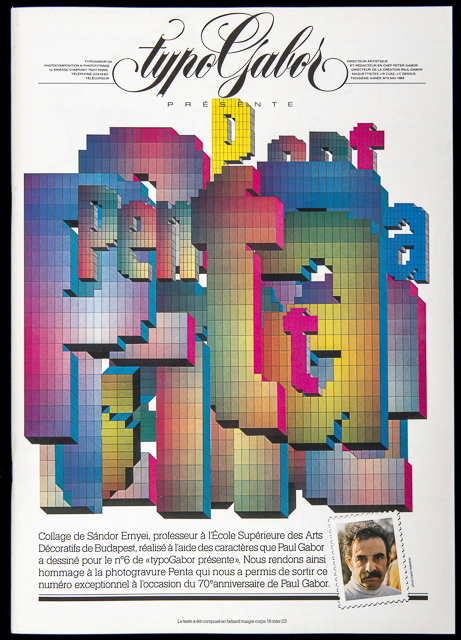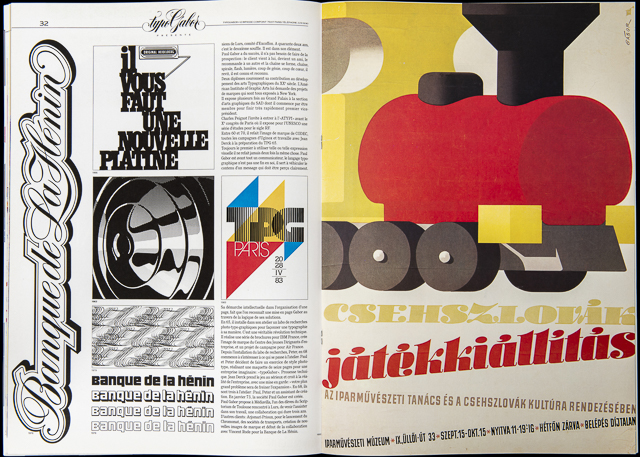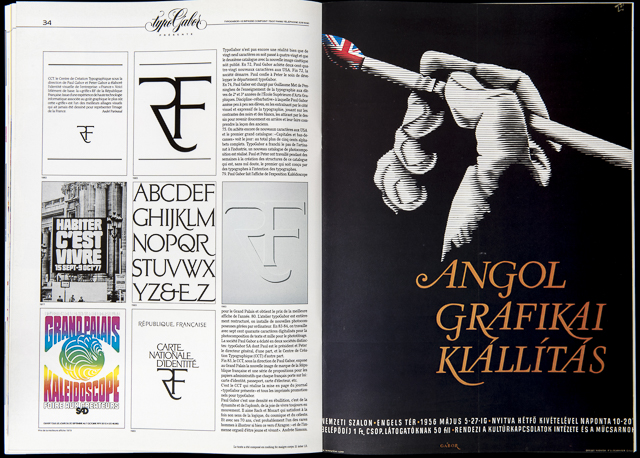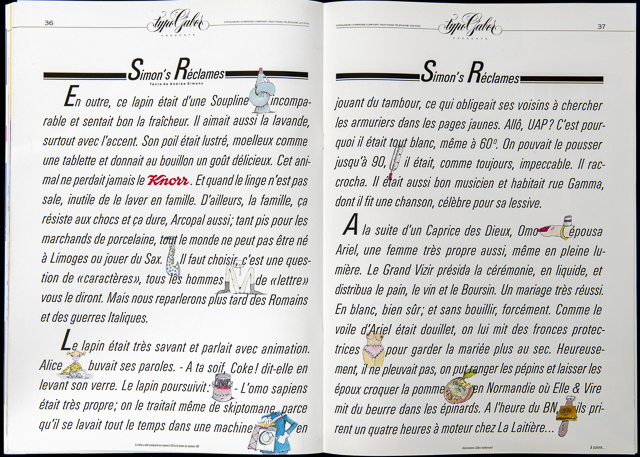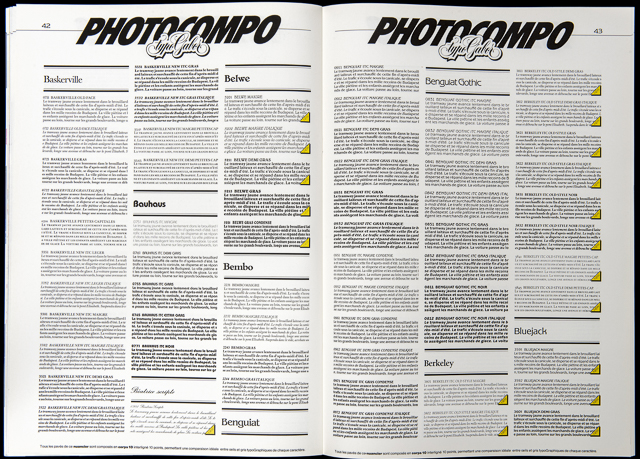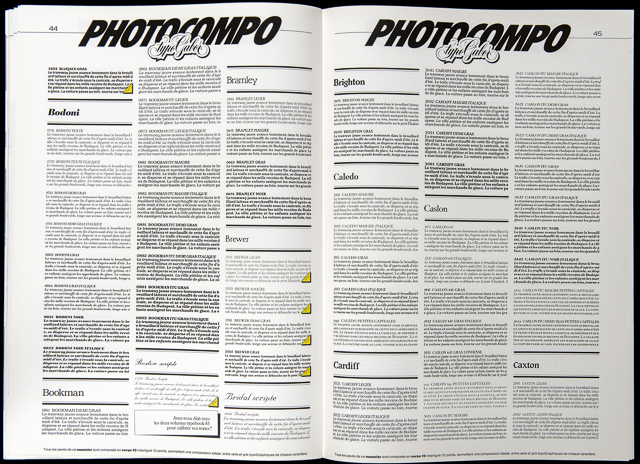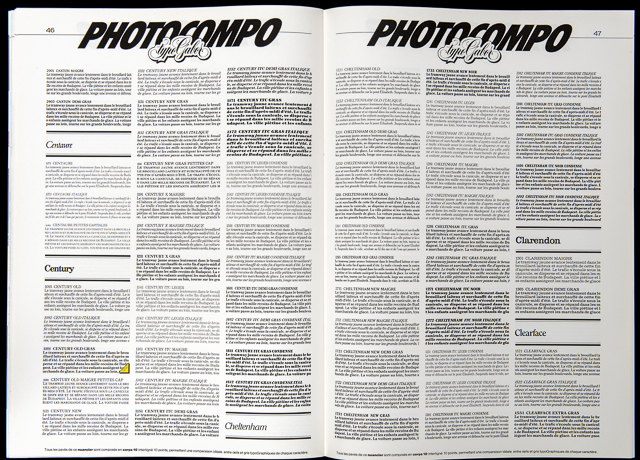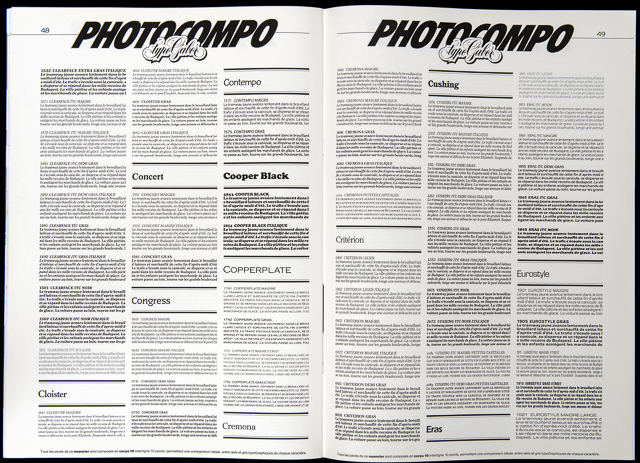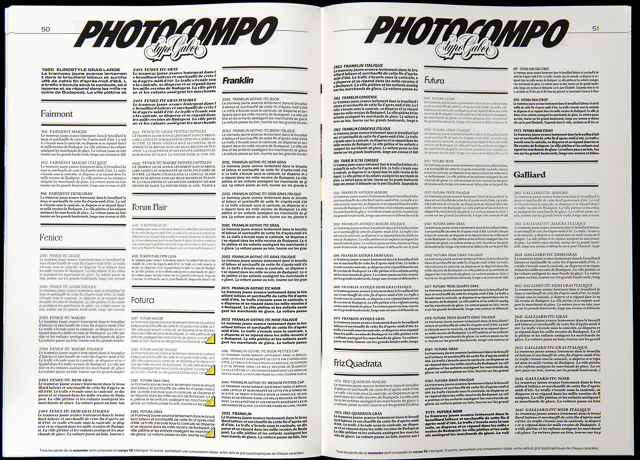
l’Histoire des Magazines typoGabor N°9 Hermann Zapf et Paul Gabor
« TypoGabor présente » N°9 Hermann Zapf et Paul Gabor
Même si certaines manifestations graphiques sont en germe dès 1968, typoGabor est fondée en 1973 par Paul et Peter Gabor. L’activité de la société est double : atelier de création graphique autour des clients historiques de Paul Gabor et société de services typoGraphiques sous l’égide de Peter Gabor.
Les premières années de typoGabor sont rythmées par le fonctionnement coûteux et limité des Diatronic de Berthold. Tant et si bien qu’à la fin des années 1970, la continuité d’exploitation semble compromise. C’est à la faveur d’une annonce dans la revue CARACTÈRE que Peter Gabor découvre l’Alphatype. Il y voit l’amorce d’une révolution du digital. Ce sera son ami (depuis) Raymond Aubry, chef d’Atelier de Graphiservice à Bruxelles qui achèvera de le convaincre. Un système de composition américain venant de Chicago, qui pour la première fois, propose non plus d’acheter mais de louer (prix dérisoire) des polices de caractères, ce qui porte l’offre et la diversité typographiques à un niveau inédit : 1 000 polices contre 80 sur Diatronic auxquels s’ajoutent 16 polices supplémentaires tous les mois.
« typoGabor présente » naît en 1980 de deux constats. Il ne s’agit plus de faire de la Pub pour une entreprise, mais d’informer et d’éduquer un marché. La Publicité. Un marché où s’affrontaient une trentaine de concurrents proposant tous à peu près les mêmes services (24 / 24, coursiers, catalogues de calibrage gratuits et qualité de composition supérieure à celle de l’édition ou de la Presse). typoGabor connaît alors le succès. Les Directeurs Artistiques affluent et les commandes doublent de volume en l’espace de 2 an. Mais la formule marketing du magazine ne plaisait plus à Peter Gabor. Il y préféra une formule nouvelle autorisant toutes les expérimentations typographiques.
Le magazine littéraire de typoGabor était né. Plusieurs directeurs artistiques vont se succéder dans les cuisines typographiques de la maison Gabor. Bill Butt, Jérôme Binda, Philippe Duriez et pour finir Paul Gabor qui revient en 89 par une magistrale œuvre consacré aux Droits de l’Homme. L’Âge d’Homme.
L’expérience de la photocomposition fut de courte durée. Le Postscript arrive sous la forme commercialisée d’Adobe Type Manager et tous les prestataires de composition perdent 50 clients par jour à partir de 1990. Peter Gabor tenta encore d’adapter son entreprise en devenant le premier compositeur qui a basculé la totalité de son fonds sur Macintosh. Mais les dettes s’accumulant et victime d’un administrateur judiciaire peu scrupuleux, il finit par baisser les bras, non sans avoir personnellement créé 4 polices de caractères pour le Journal Libération en 1994.
Une aventure de vie passée à promouvoir la diversité et la qualité de composition, parce que comme l’aimait à rappeler son père Paul, d’après une phrase de Jean Cocteau : « Le style n’est pas une danse mais une démarche ».
L’illustration basée sur l’alphabet « numérique » de Paul a été réalisée par Sándor Ernyei lors d’une visite à Paris (cliquez sur la photo pour voir les détails).
Ce magazine va clore le chapitre des publications « traditionnelles » du magazine « typoGabor Présente ». Il avait quelque chose de tragique pour moi. Mise en œuvre au début de l’année 84 et publié en mai, soit 2 mois 1 / 2 avant le décès de ma mère Klara Gabor le 13 août 1984. Paul quant à lui venait d’avoir une alerte cardiaque en 1983. Ce faisant la famille, ma seule famille se fragilisait et l’immense amour que j’avais pour l’un et l’autre me dictait un devoir de mémoire de leur vivant. J’allais donc consacrer l’édition de ce magazine à l’œuvre de Paul. Mais je me devais de l’équilibrer. Ne voulant pas en faire un livre de deuil mais plutôt une référence à la gloire des grands typographes contemporain. J’ai appelé à la rescousse Fernand Baudin à Bruxelles. Il a écouté et approuvé. Nous avons convenu d’un voyage à Darmstadt pour aller rencontrer à trois (Fernand, Paul et moi-même) Hermann Zapf pour l’interviewer sur son œuvre.
La maison d’Hermann Zapf. Un choc. Une battisse toute blanche, carrée. Construite autour d’un patio sur lequel toutes les pièces donnaient par des vitres. De fait la maison était illuminée autant vers l’intérieur que vers l’extérieur qui donnait sur la lisière d’un bois. Les pièces étaient immenses. On allait d’un espace vers l’autre sans porte, juste des ouvertures. On pouvait évoquer une construction à la Bauhaus, mais aussi bien une maison à la japonaise. Ça n’était pas un musée, mais plutôt un lieu de travail et de réflexion. Hermann nous amena dans son bureau et là il nous reçut et nous donna un cours de typo. Il prit son stylo à bille et nous écrivit un texte en Garamond corps huit avec juste un outil que chacun de nous utilise tant bien que se peut. Mais Zapf avait la maîtrise. L’outil comptait peu. Sa main, sûre, caressait le papier avec une dexérité, une assurance que je n’avais jamais vu. Je connaissais Hermann pour l’avoir rencontré souvent à Lurs, lors des Rencontres de Lure de 1963 à 1968. Pour l’avoir également croisé plusieurs fois lors des assemblées générales de l’ATYPI. Mais là, au cœur de son atelier-maison-havre de paix et de travail, il se révélait tel qu’en lui-même. Simple, humaniste et plein d’humour.
Me souviens à un moment lui avoir demandé ce qu’il pensait de la mode des approches serrées très en vogue dans les compositions publicitaires, mais aussi dans l’œuvre de Lubalin… Sa réponse fusa comme un éclat de rire. Ah, le Sex Spacing TypoGraphy ? Il avait tout dit. En une phrase courte et lapidaire.
Cette visite restera et pour moi mais aussi pour Paul, un souvenir mémorable. Je n’étais pas si surpris que ça. Mais j’ai eu la confirmation d’une intuition. Le travail, le travail. Il n’y a pas d’autre voie. Et Zapf en avait fait son mode de vie. Sinon sa religion.
Pour celles et ceux qui s’en souviennent, des maquettes en couleur, nous avions connu cela déjà avec le ColorKey de la 3 M et là, tout à coup au début des années 80 nous découvrons les vertus du transfert. De la compo (Titrage ou Texte) transférable en couleur sur des maquettes. Bien évidemment ce sont d’abord les studios de Packaging qui ont utilisé cette technique en premier. Suivis par les Agences de Publicité qui pouvaient enfin montrer des maquettes en Réalité Colorée à leurs clients. Juste pour mémoire, il s’agissait d’une technique très instable et fort coûteuse. Nos techniciens s’arrachaient leur touffe de cheveux pour livrer en temps et en heure des typos en couleur.
Et donc voilà l’interview du Maître. Hermann Zapf. Je vous invite à cliquer sur les pages pour lire en format réel les texte et découvrir les illustrations en grandeur nature. Un plaisir de l’intellect.
Et ici une fiction-caricature de l’univers impitoyable de la Publicité, d’Andrée Simons, prématurément disparue en 1983 que j’ai connu entre-autre grâce à Albert Boton. Immense talent que cette jeune femme.